2023 年 16 种最佳贴纸字体(免费和付费)
已发表: 2023-11-28您是否曾经努力为您的图形设计项目寻找完美的字体? 您是否希望为您的设计增添一点创造力和独特性?
好吧,别再犹豫了,因为在这篇博文中,我们将探索最好的贴纸字体,将您的设计提升到一个新的水平!
在本文中,我们将深入研究贴纸字体的世界,并展示一些肯定会吸引您眼球的令人难以置信的选项。
我们不仅会为您提供多种字体可供选择,还会分享有关每种字体的一些有趣的统计数据和事实,让您有信心做出明智的决定。
因此,如果您准备好增强您的设计项目并用迷人的贴纸字体让您的观众惊叹不已,请继续阅读!
我们将分享您需要了解的有关这些字体的所有信息,并在此过程中为您提供宝贵的提示和见解。 准备好探索贴纸字体的奇妙世界,并将您的设计变成杰作!
最佳高级贴纸字体
希望为您的贴纸项目添加一些出色的字体来提高您的设计水平? 别再犹豫了! 在本节中,我们将重点介绍最好的优质贴纸字体,它们一定会为您的设计增添额外的创造力和独特性。
那么,为什么还要等呢? 深入研究并发现完美的字体,将您的项目提升到一个新的水平!
塞凯克
Sekek 是一种可爱的显示字体,散发着俏皮和真实的气息。 它是儿童活动和学校项目的理想选择。 Sekek 凭借其迷人的设计,为任何设计项目带来令人愉悦的感觉。
这种字体旨在捕捉乐趣和兴奋的本质。 其俏皮的曲线和古怪的细节使其非常适合吸引年轻观众的注意力。
无论您是设计生日邀请函、课堂海报还是儿童读物封面,Sekek 都会增添额外的魅力和奇思妙想。
Sekek 的突出特点之一是其真实性。 它具有手绘的感觉,为您的设计增添个性和有机的触感。 这种字体给人一种温暖和平易近人的感觉,使其成为创建引人入胜且相关内容的绝佳选择。
涂鸦贴纸
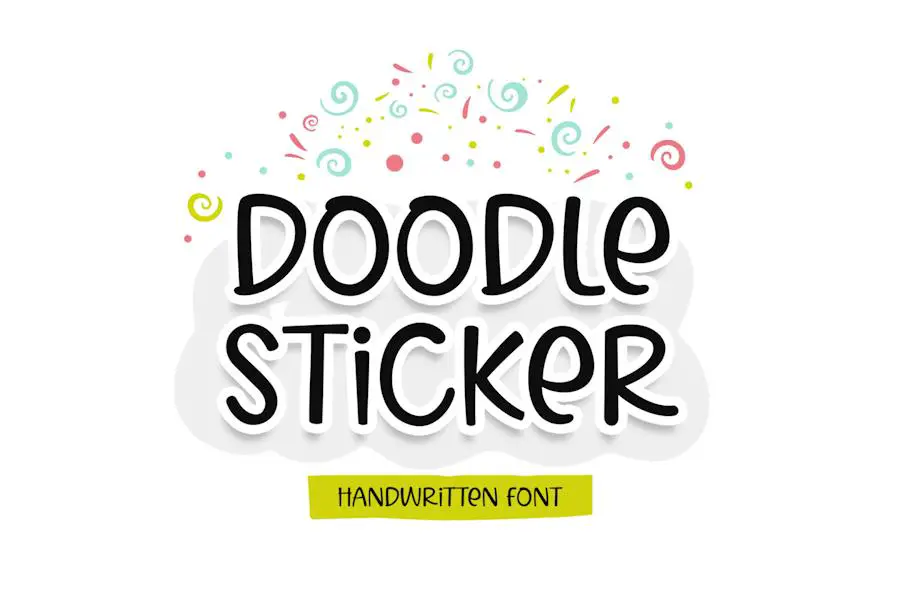
Doodle Sticker 是一款俏皮而时尚的无衬线字体,可为任何项目增添一丝优雅和现代感。 其美丽而优雅的设计使其非常适合各种平面设计项目。
凭借其俏皮的氛围,涂鸦贴纸为您的设计带来有趣和创意的元素。 无论您是设计徽标、海报还是社交媒体图形,这种字体一定会吸引眼球并使您的项目脱颖而出。
该字体的无衬线风格赋予其干净和现代的外观,而其俏皮的触感增添了独特的风格。 它在现代与精致之间取得了完美的平衡,使其具有多种设计用途。
燕麦杰克
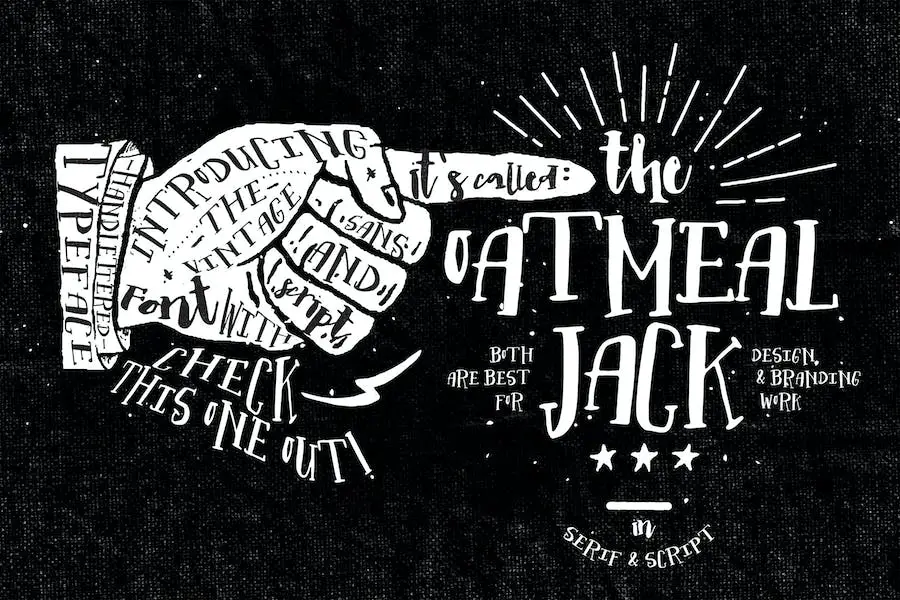
Oatmeal Jack 是一种独特的字体,结合了脚本和衬线字体的风格。 它是手写的,给人一种充满活力和真实的感觉。 该字体是使用画笔和记号笔创建的,为其设计增添了个人风格。
借助 Oatmeal Jack,图形设计师可以使用既具有视觉吸引力又独特的字体来增强他们的项目。
无论是用于徽标、品牌推广还是其他创意活动,这种字体都一定能彰显个性。 其手工制作的特性为任何设计增添了创造力和原创性。
赛博戈尔贡
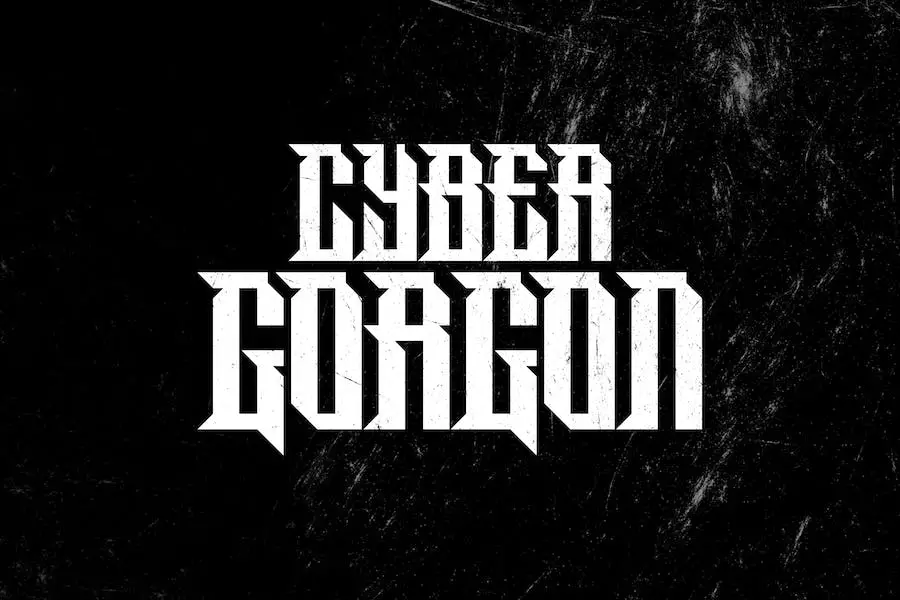
Cyber Gorgon 是一种专门为创建赛博朋克主题的团队或社区徽标而设计的字体。 它提供了独特而时尚的外观,可以增强任何图形设计项目。
借助 Cyber Gorgon,您可以为您的设计添加未来感,使它们脱颖而出。 该字体的时尚和前卫美感完美地捕捉了赛博朋克流派的精髓,为您的徽标带来超酷和现代的感觉。
这种字体非常适合希望通过赛博朋克风格提升其项目的图形设计师。 无论您是为游戏团队、科技公司还是未来社区设计徽标,Cyber Gorgon 都能提供完美的排版,让您的愿景成为现实。
兰博斯
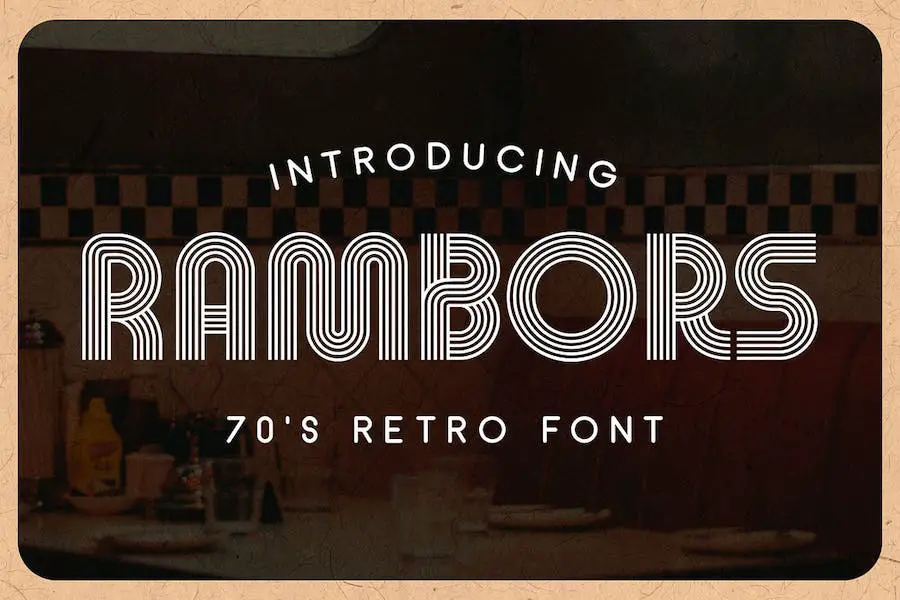
Rambors 是一种多行显示字体,可为您的设计带来 70 年代的气息。 这种字体的灵感来自于复古美学,为您的项目增添了有趣的未来元素。
Rambors 凭借其独特且引人注目的设计,非常适合希望增强创意工作的平面设计师。 无论您是在制作贴纸、海报还是任何其他设计项目,这种字体一定会给人留下深刻的印象。
Rambors 的突出特点之一是它的多行显示。 这意味着每个字母都由多行组成,创造出视觉上引人注目的动态效果。
使用 Rambors,您可以轻松地为文本添加深度和维度,赋予其现代而迷人的外观。 告别无聊、扁平的字体,迎接全新水平的图形设计。
戈德·奎克
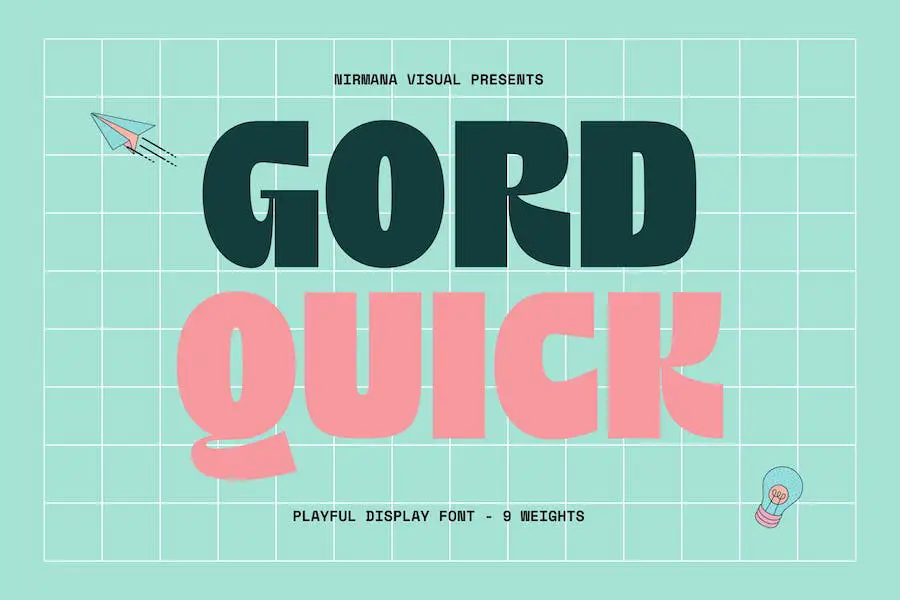
Gord Quick 字体是一种独特且有趣的无衬线衬线字体家族,有 9 种不同的粗细。 该字体具有广泛的粗细范围,为希望改进项目设计的图形设计师提供了多功能性和灵活性。
无论您是要创建贴纸、徽标还是其他视觉元素,Gord Quick 都能满足您的需求。
Gord Quick 字体系列的每种粗细都带来了自己独特的风格和特征。 无论您需要大胆、引人注目的设计还是更微妙、优雅的外观,这款字体的粗细都能满足您的需求。
不同的重量使您能够创造出具有凝聚力且具有视觉吸引力的设计来吸引观众。
各种各样的
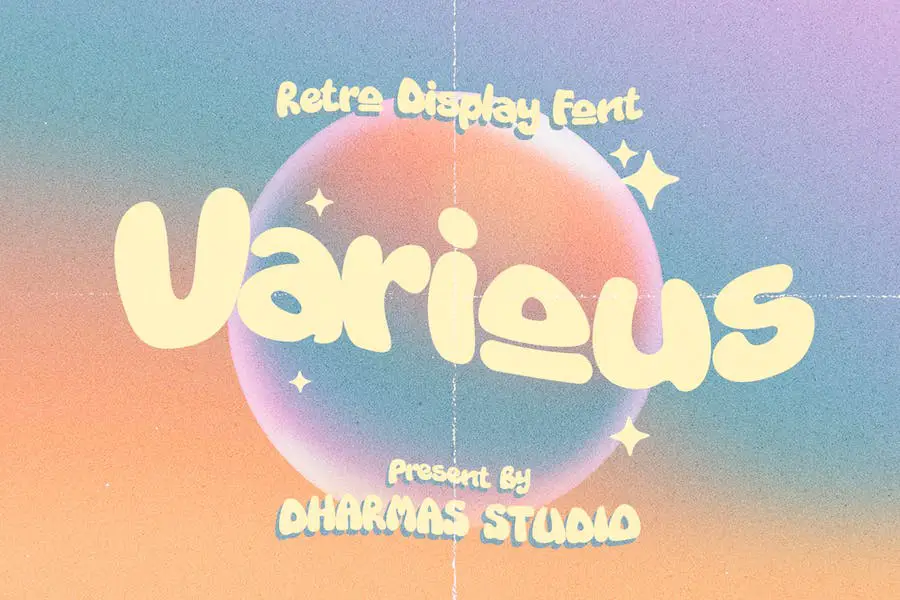
Different 是一种独一无二的字体,可为任何项目带来新鲜和怀旧的感觉。 这款定制字体采用 00 年代风格设计,从复古和手绘复古标志中汲取灵感。
借助各种,您可以立即将您的设计带回到过去,唤起怀旧感和魅力。 该字体独特的外观为任何文本增添了个性和个性,使其非常适合海报、徽标甚至社交媒体图形。
《Various》的与众不同之处在于它对细节和真实性的关注。 每个字母都经过精心制作,类似于过去的手绘标志,确保了现实和复古的美感。
无论您的目标是复古氛围还是只是想为您的设计添加一点独特性,这款字体都能满足您的需求。
师父您好
Hello Master 是一种时尚且现代的脚本字体,称为“It Script This type”,可为任何设计项目增添独特的触感。 凭借其不规则的基线,该字体脱颖而出,为您的设计带来额外的优势。
Hello Master 字体拥有现代而时尚的外观,非常适合想要以优雅和创造力来增强其项目的图形设计师。 其不规则的基线增加了视觉趣味元素,使您的文字引人注目并吸引观众的眼球。
Hello Master 的显着特征之一是它的多功能性。 无论您是在设计徽标、品牌材料、包装设计,甚至是社交媒体图形,这种字体都可以轻松适应任何环境,并将您的设计提升到一个新的复杂水平。
乌鸦地狱回合
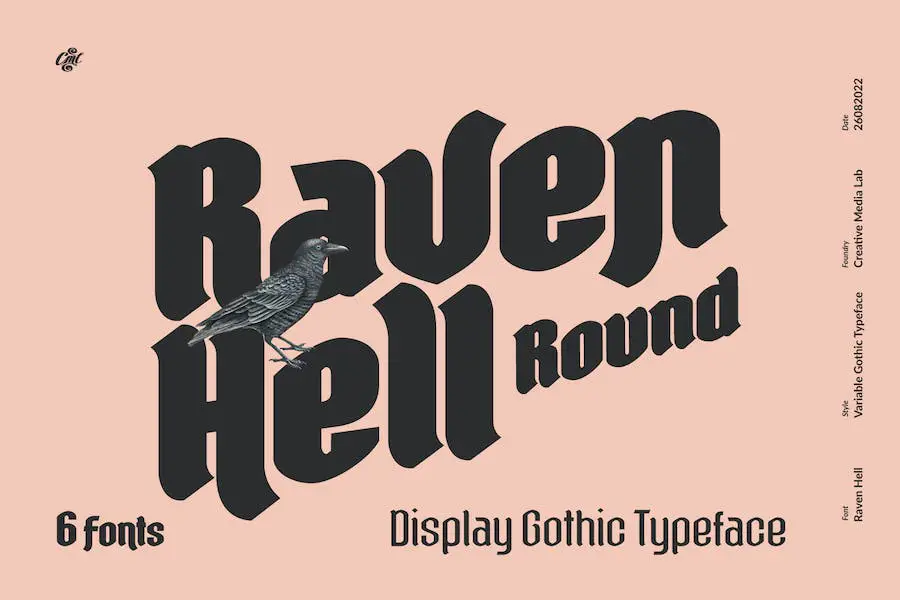
Raven Hell Round 是一款简单的哥特式字体,提供从细到黑色的 6 种风格。 该字体非常适合为您的图形设计项目添加一丝黑暗和前卫感。
凭借其时尚的设计,一定会增强您作品的整体美感。 无论您是在制作海报、徽标还是任何其他设计项目,Raven Hell Round 都将提供独特而引人注目的外观。
凭借其多种风格,您可以轻松尝试并找到最适合您的项目的款式。 从优雅的细线到大胆而有影响力的黑色字母,这种字体拥有一切。
无论您想要哪种风格或基调,Raven Hell Round 都一定能帮助您实现它。 凭借其哥特式魅力,它为您的设计增添一丝神秘感和吸引力。
因此,如果您是一名图形设计师,希望提升项目的外观和感觉,那么这种字体绝对值得考虑。 Raven Hell Round 为您的设计带来黑暗而迷人的边缘。
邦迪显示器
Bondist Display 是一种多功能字体,可以提升任何项目的设计。 凭借其广泛的风格,它为平面设计师提供了无限的可能性。 无论您想要创造现代前卫的设计,还是俏皮异想天开的设计,Bondist Display 都能满足您的需求。
Bondist Display 的主要特点之一是其适应性。 它可以无缝地融入各种设计风格,使其成为寻找能够满足不同审美偏好的字体的设计师的首选。
从优雅精致到大胆引人注目,Bondist Display 可以轻松增强任何设计的视觉吸引力。
Bondist Display 不仅用途广泛,而且还提供多种字符和字形选择。 这使得设计师可以尝试不同的印刷元素,并为他们的项目添加独特的风格。
穆赞比克
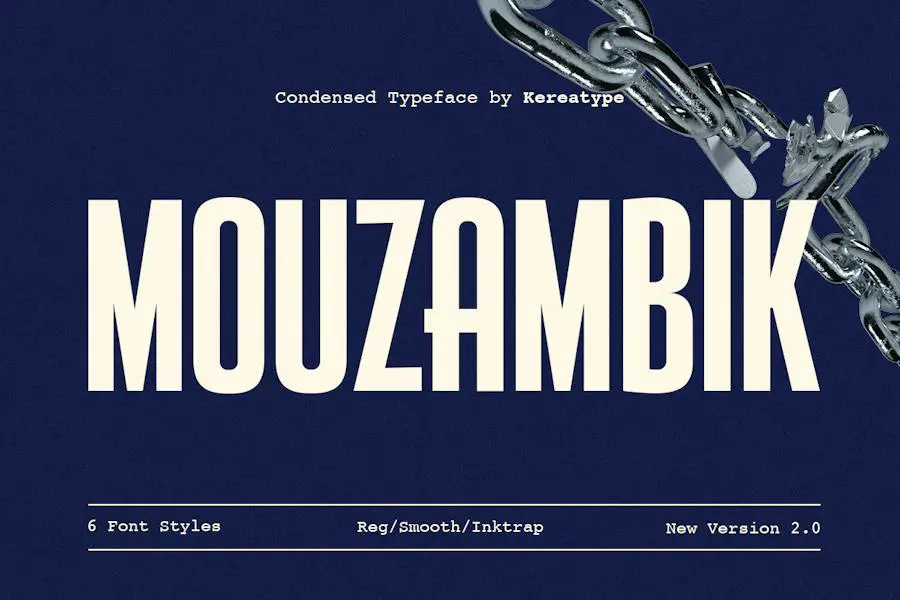
Mouzambik 是一种出色的字体,可为任何设计项目增添一丝大胆和复杂性。 这种简单、简洁的无衬线字体非常适合希望将项目提升到新水平的图形设计师。
凭借其独特的个性,Mouzambik 无疑会让您的设计脱颖而出。
这种字体拥有干净简约的风格,但它仍然设法传达出一种大胆和复杂的感觉。 它的简单性让设计中的其他元素脱颖而出,而其简洁的性质确保它不会压倒整体构图。
无衬线风格赋予其现代和时尚的感觉,使其非常适合各种设计项目。
Mouzambik 的突出特点之一是它能够吸引注意力。 字体的大胆使其立即引人注目,吸引观众并引起他们的注意。
无论您是在创建徽标、网站还是任何其他设计作品,使用 Mouzambik 都会立即提升您的作品并给人留下持久的印象。
最好的免费贴纸字体
希望用一些引人注目的贴纸字体来增强您的设计? 别再犹豫了! 在本文中,我们收集了最好的免费贴纸字体,它们将使您的项目更上一层楼。 你还在等什么? 深入研究并发现适合您下一次创意尝试的完美字体!
贴纸
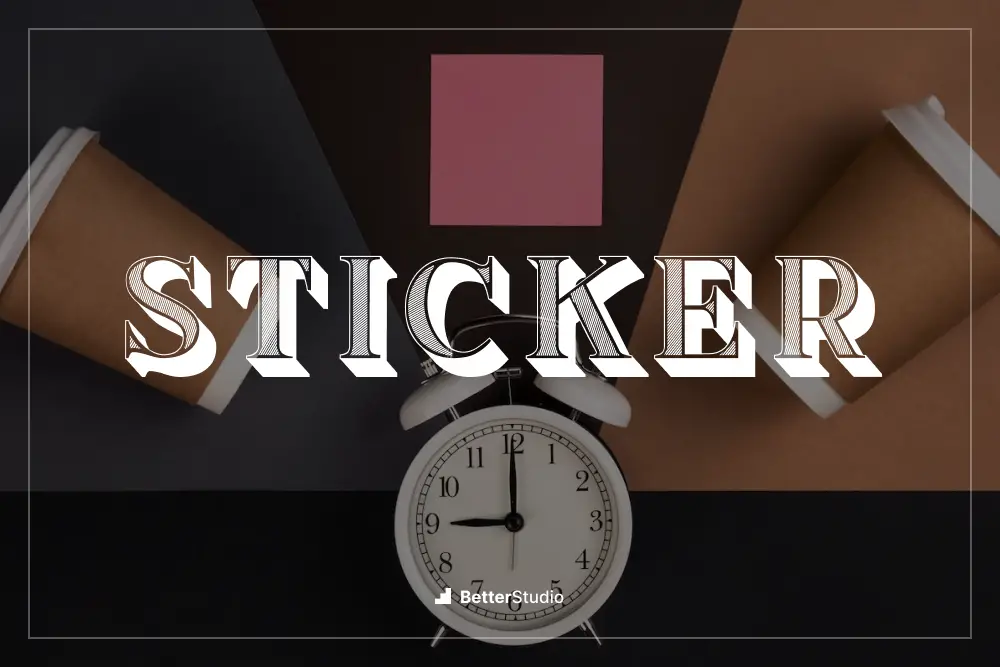
Vladimir Nikolic 的 Sticker 是一款改变游戏规则的字体,每个图形设计师的工具箱中都需要拥有它。 其独特而引人注目的设计为任何项目增添了有趣和俏皮的感觉。
Sticker 具有多种风格和变化,使设计师能够轻松创造令人惊叹和难忘的视觉效果。 无论您是在制作徽标、海报还是网站,这种字体都会将您的设计提升到一个新的水平。
它的多功能性和创造力使其成为任何想要提升项目水平的设计师的必备品。 此外,凭借其易于使用的界面和无缝集成,使用 Sticker 变得轻而易举。 不要错过使用这种出色的字体来增强您的设计游戏的机会。
纸贴纸
Kurnia Setyadi 的 Paper Sticker 是一种图形设计师可以用来增强其项目设计的字体。 凭借其独特且引人注目的风格,该字体非常适合创建引人注目的贴纸。
纸贴纸的突出特点之一是它的多功能性。 它可用于各种设计项目,从标志设计到包装标签。 该字体简洁粗体的线条使其易于阅读,确保您的信息能够清晰地传达给受众。
纸贴纸的另一个特点是其俏皮和有趣的美感。 该字体具有手绘外观,赋予其独特的个人风格。
无论您是为俏皮的儿童品牌还是时尚活动设计贴纸,这款字体都会为您的项目增添一丝奇思妙想和创造力。
黑色贴纸
Scratchones 的 Black Sticker 是一款出色的字体,可以提升任何项目的设计。 它具有时尚的外观,非常适合寻求为作品增添精致感的平面设计师。
Black Sticker 凭借其简洁的线条和大胆的美感,成为创建引人注目的贴纸的首选字体。
Black Sticker 与其他字体的区别在于它的多功能性。 它可用于广泛的设计项目,从徽标和品牌到包装和社交媒体图形。
该字体的锋利边缘和现代设计使其成为现代和简约风格的绝佳选择。 无论您是从事企业项目还是有趣且充满活力的设计,Black Sticker 都将带来理想的效果。
孟买贴纸
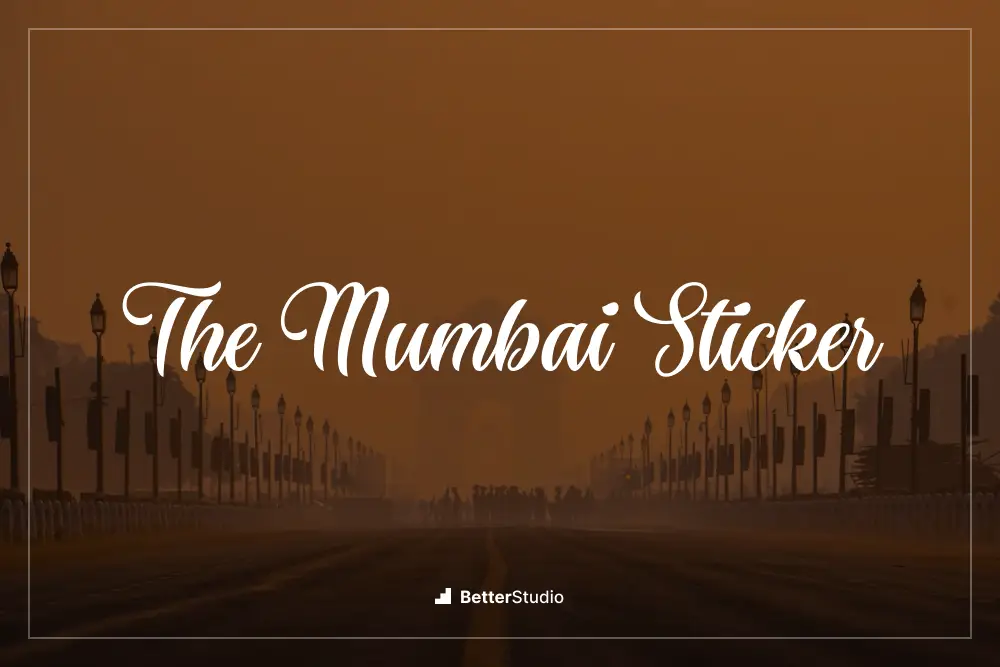
由 Roland Huse Design 设计的 Mumbai Sticker 对于希望增强其项目设计的图形设计师来说是一款绝佳的字体。 这种字体非常适合为任何设计增添创意和独特性。
凭借其大胆而引人注目的设计,孟买贴纸一定会让您的项目脱颖而出。
选择正确的贴纸字体取决于您项目的风格和主题。 考虑您想要传达的整体基调以及您想要通过贴纸传达的信息。 如果您想要一种有趣和俏皮的氛围,请选择具有大胆和异想天开的设计的字体。
为了获得更加优雅和精致的外观,请选择具有时尚和现代风格的字体。 在做出最终决定之前,测试不同的字体并看看它们如何适合您的设计也是一个好主意。
是的,您绝对可以自定义贴纸字体,使其更加独特和个性化。 许多图形编辑软件和设计工具允许您调整字体的大小、颜色和其他属性。
您还可以组合多种字体来创建适合您偏好的自定义外观。 不要害怕尝试并发挥贴纸字体的创意!
结论
总之,我们讨论了可以极大增强项目设计的最佳贴纸字体。 从俏皮、异想天开到大胆、引人注目,这些字体一定会让您的贴纸脱颖而出。